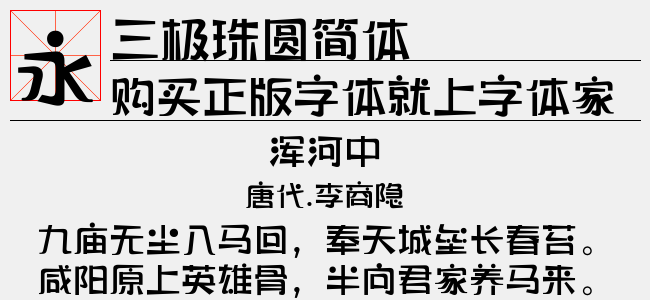
三极珠圆简体 字体大小2.29 M,包含了6763个汉字以及附加其他英文字体和阿拉伯数字,属于三极字库。三极珠圆简体(TTF)可以付费下载,商业用途请购买版权,它的特征就是印刷,个性,海报,标题,采用安装嵌入的安装方式,支持符号拉丁文日文中文等语言
字体作者:三极字库
字体名称:三极珠圆简体
字体家族:三极系列